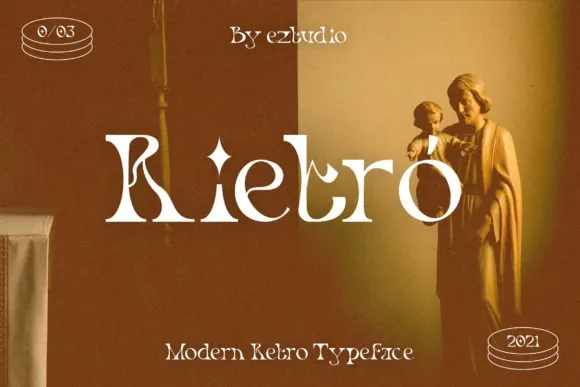
Rietro Font – Download Grátis
A Rietro Font é uma elegante tipografia serifada, lançada pelo site de design 99designs. Seu estilo peculiar e quirk com curvas únicas criam um fluxo mágico que chama atenção. O designer, eztudio, criou esta fonte moderna e sofisticada, perfeita para a criação de logotipos, identidades corporativas, convites e embalagens de presente, além de designs de casamento, postagens nas redes sociais e muito mais. Esta é uma fonte ideal para quem procura um estilo elegante que irá destacar seu trabalho em qualquer projeto gráfico.